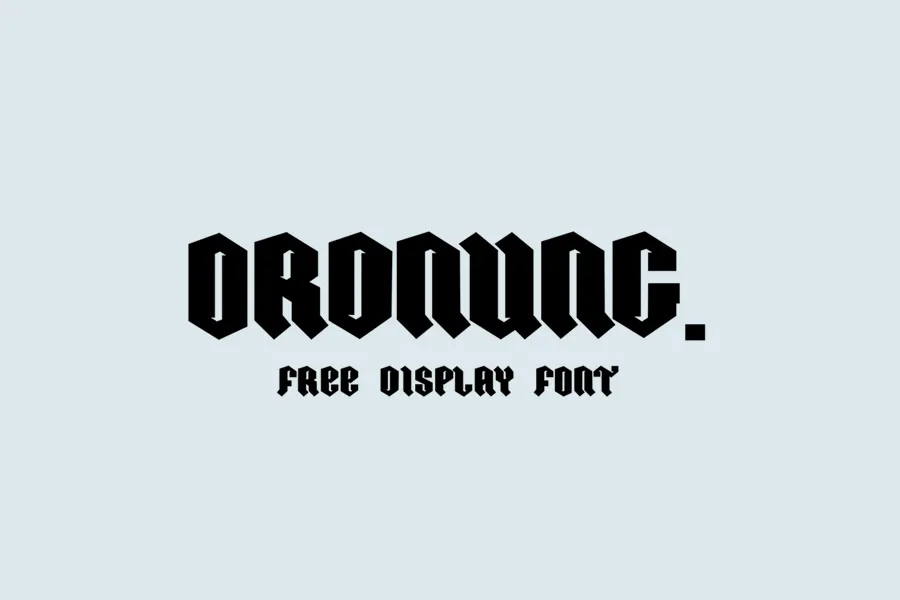
Ordnung é uma fonte Gothic modular que transmite a elegância moderna através de sua estrutura curvilínea forte, sua textura pesada e seu olhar áspero. Ideal para uso em cabeçalhos, aplicações de logomarcas ou insígnias, esta fonte é perfeita para qualquer projeto que exija um estilo clean e moderno. Suas linhas leves e sua aparência pura podem ser facilmente personalizadas para criar designs únicos e memoráveis. Ordnung é a escolha ideal para artistas gráficos em busca de uma fonte que brilhe na tela ou se destaque nas ruas, seja no design de camisetas, faixas de propaganda ou até mesmo como um elemento distintivo para badges. Em conjunto com sua natureza clean e moderna, Ordnung é uma excelente opção para designers em busca de uma fonte que combina elegância com força. Sua modularidade permite que seja ajustada facilmente para diversos usos, tornando-a perfeita não apenas para os principais tópicos ou cabeçalhos, mas também para qualquer elemento do design gráfico que se destine a destacar. Ideal tanto para projetos digitais quanto offline, Ordnung é uma escolha inteligente para quem busca um estilo clean e moderno na sua próxima criação visual.